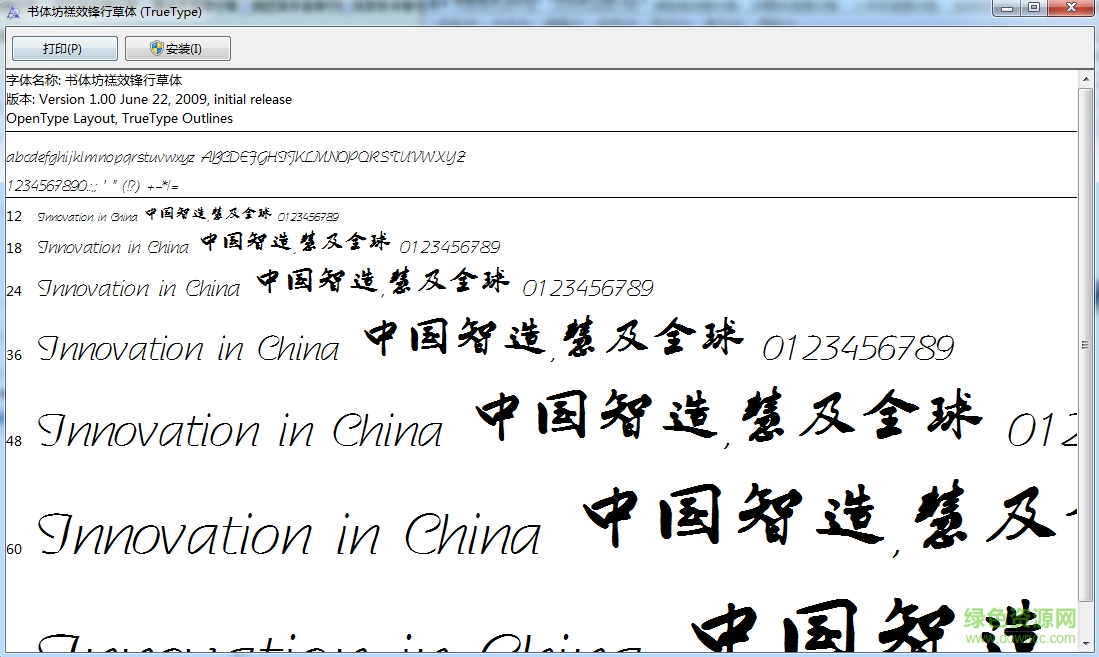
scfzxfxs
scfzxfxs是什么字體?scfzxfxs就是書體坊禚效鋒行草體字體,該字體筆勢(shì)連綿回繞,結(jié)構(gòu)精簡,馳騁肆意,本站為大家免費(fèi)提供這款行草字體的下載地址!
行草字體介紹
行草,是介于行書、草書之間的一種書體和書法風(fēng)格,可以說是行書的草化或草書的行化。它是為了彌補(bǔ)楷書的刻板和草書的難于辨認(rèn)而產(chǎn)生的。行書大約是在東漢末年產(chǎn)生的。
scfzxfxs字體